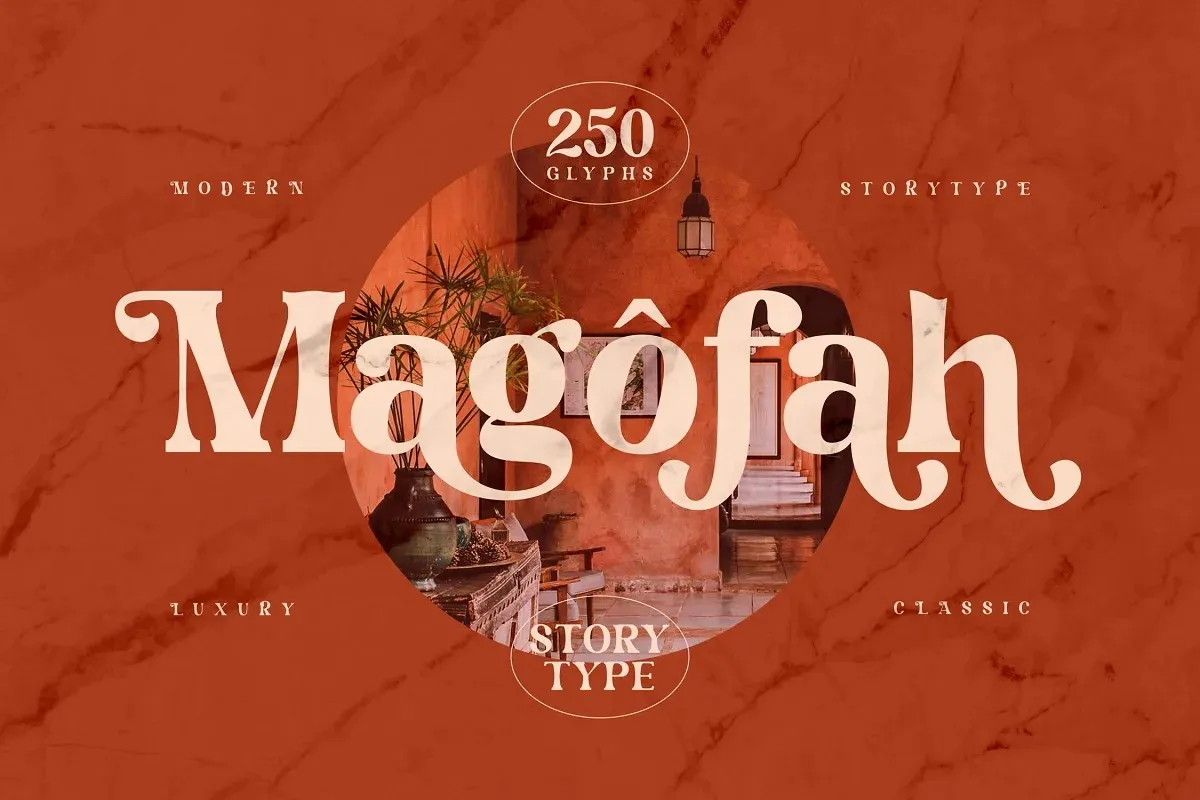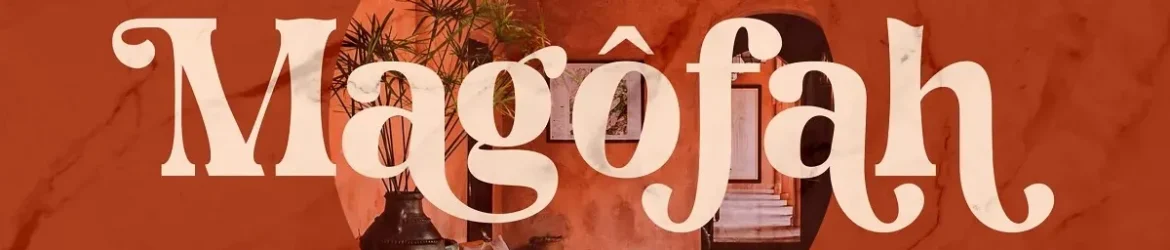
A ‘Magofah Font’ é uma elegante serif que se destaca por sua simplicidade moderna e detalhes refinados. Desenvolvida pelo Storytype Studio, esta fonte é perfeita para aqueles que desejam dar vida a suas ideias em um design visual impactante. Suas linhas finas e robustas proporcionam ao texto uma aparência sólida e confiável, ideal para criar designs de alta qualidade e estilosas gráficas. Em uma era onde muitos preferem fontes mais clean e minimalistas, a ‘Magofah Font’ oferece um contraponto perfeito com suas nuances sofisticadas, tornando-a uma escolha única em sua categoria de serif fonts. Sem sombra de dúvida, é o ideal para aqueles que buscam uma combinação envolvente de modernidade e elegância em seus projetos visuais.